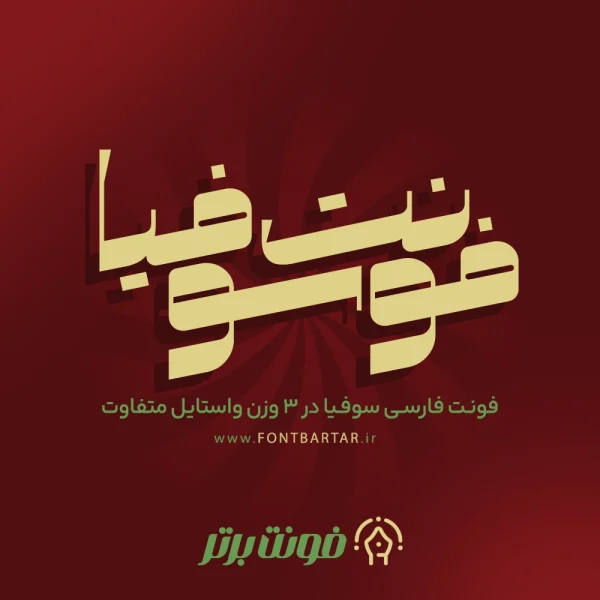
فونت تایپوگرافی سوفیا
فونت جدید سوفیا
Sofiya Font
فونت لوگوتایپ سوفیا جدیدترین فونت ارائه شده در سایت فونت برتر است. این فونت قابلیت استفاده در تمامی موارد تبلیغاتی، عناوین کودکانه، نمایشی، مطبوعاتی، لوگوتایپ را داراست. با توجه به سنگینی زیاد در فونت لوگو سوفیا، نادیده گرفتن آن نسبت به مواضع دیگر گرافیکی بسیار سخت می شود و این به خودی خود نکته ای مثبت است. فونت های فوق سنگین (یا به اصطلاح super heavy)، فونت جدید سوفیا بسیار مناسبی برای تیترها و موارد تبلیغاتی به حساب می آیند و تاثیرگذاری بالایی بر ذهن مخاطبان خود دارند.
فونت فارسی سوفیا که خود فونتی فوق سنگین محسوب میشود، در لوگوتایپ هم قابلیت استفاده دارد و برای تیتر روزنامه ها و مطالب با اهمیت بالا، از جدیت کافی برخوردار است و پیشنهاد می شود.
وزن های فونت حرفه ای سوفیا:
وزن های فونت سوفیا
فونت فارسی خاص سوفیا جدیدترین فونت ارائه شده در وبسایت فونت برتر است. هدف از ساخت این فونت، ایجاد حروفی سنگین با روحیه ای نسبتا هندسی است، هندسی بودن حروف فونت زیبا سوفیا همراه با لبه های نسبتا صاف و شیار های کم، این امکان را می دهد که ساختار کلی فونت به خوبی خود را در متون بزرگ و با اهمیت بالا نشان دهد.